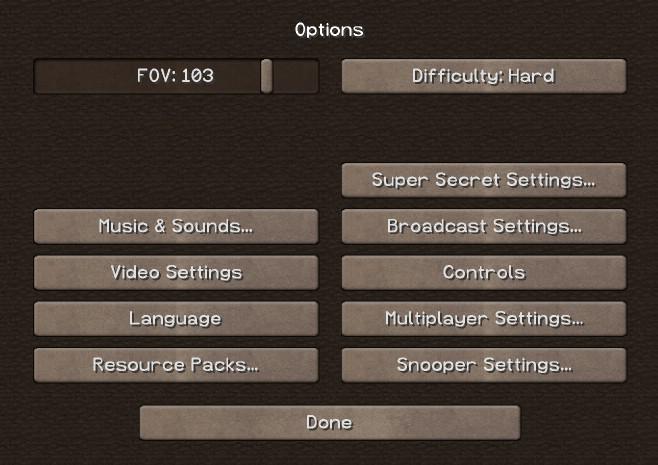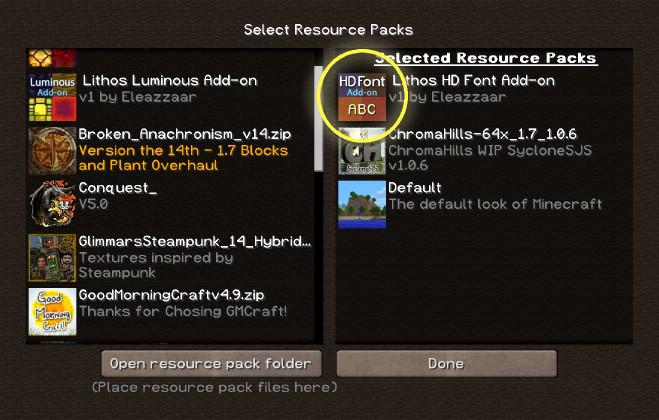
Lithos HD Font Категория: Скачать / Ресурпаки / Ресурспаки для Minecraft 1.9 Описание Маленький аддон к текстурам, который добавит в игру HD-шрифт. Minecraft станет выглядеть чуточку опрятней. Скачать lithos-hd-font-add-on-1.9.zip [46.92 Kb] (cкачиваний: 68) Скриншоты